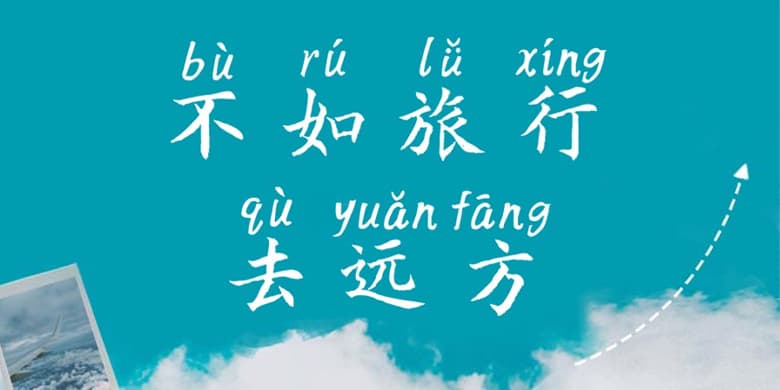
顾建平楷书体加拼音,由新加坡杰出贡献奖、文化艺术奖获得者,书法家、文字学家顾建平创作。字体沉稳谨严、秀丽劲健,乃唐楷精髓与作者个性完美结合之艺貌。
该字体潇洒大气的笔触,端庄持重的设计,都让人耳目一新,焕发出新的活力!是一款用途十分广泛的方正书法楷体字体,非常适合用作印刷字体,以及文化类宣传设计、商业类品牌广告和产品包装设计。